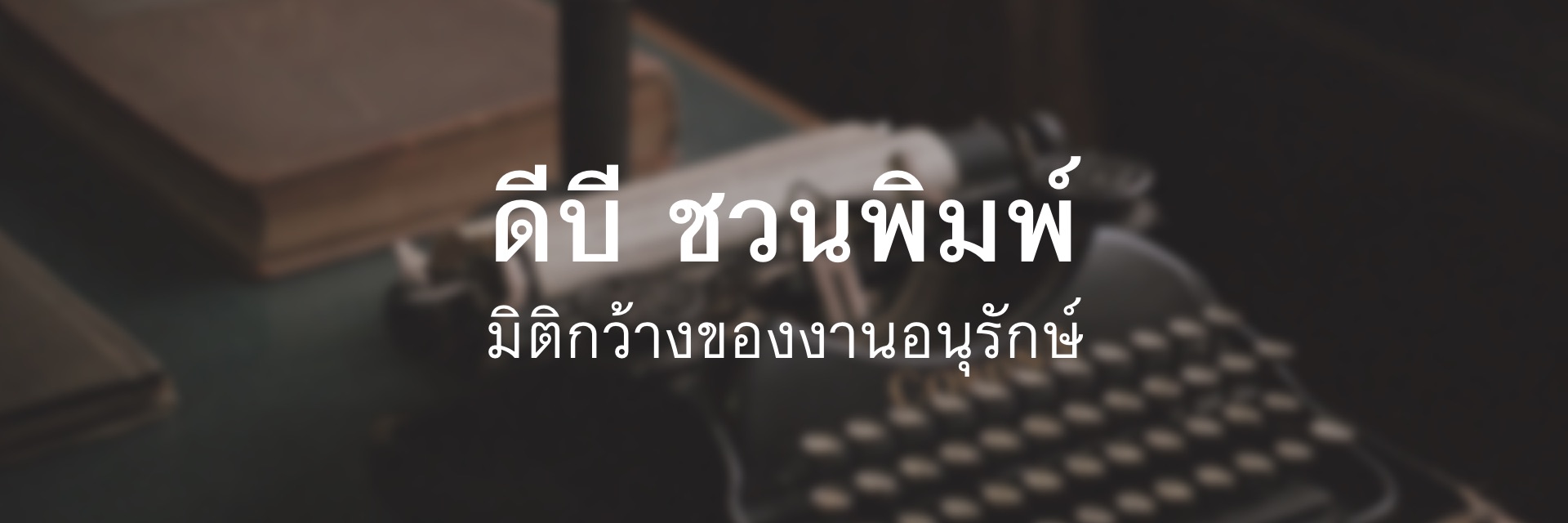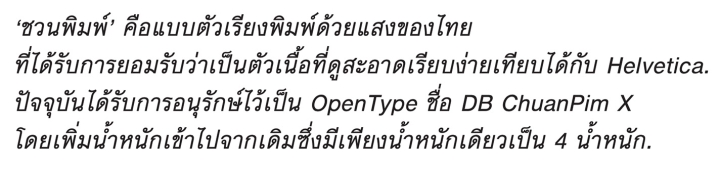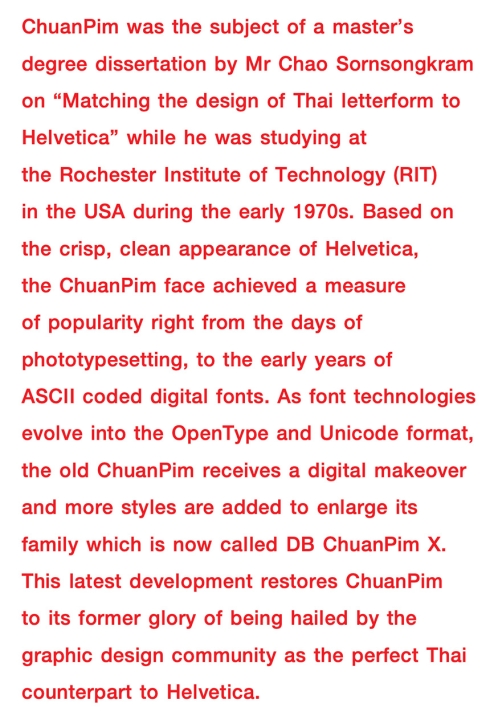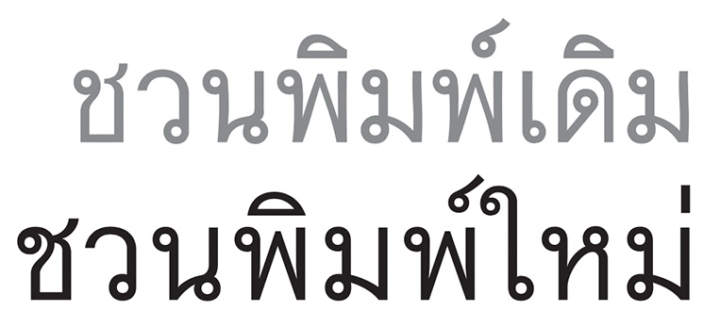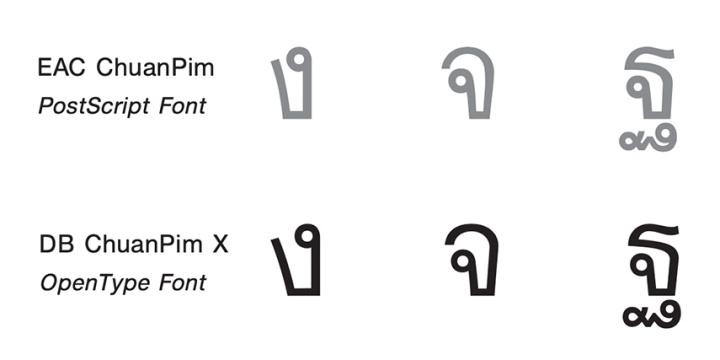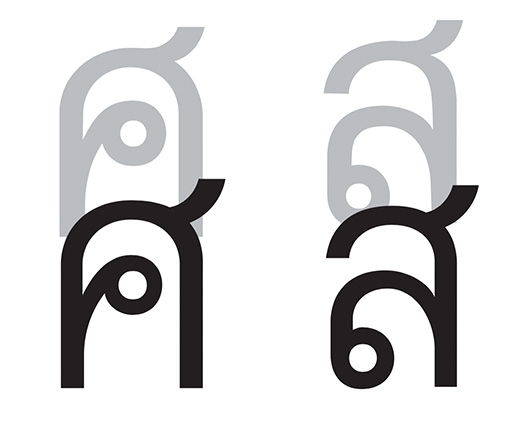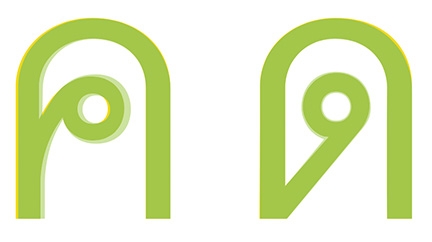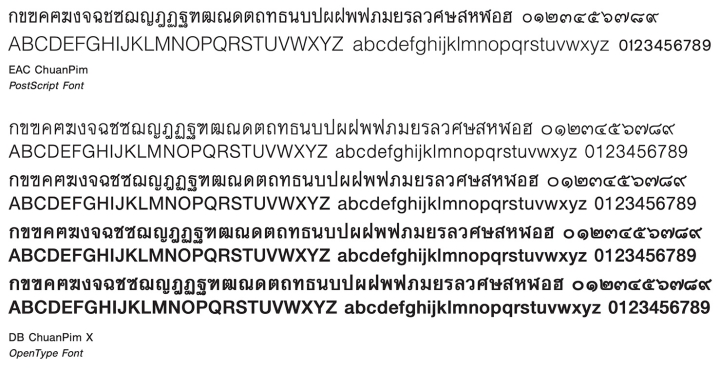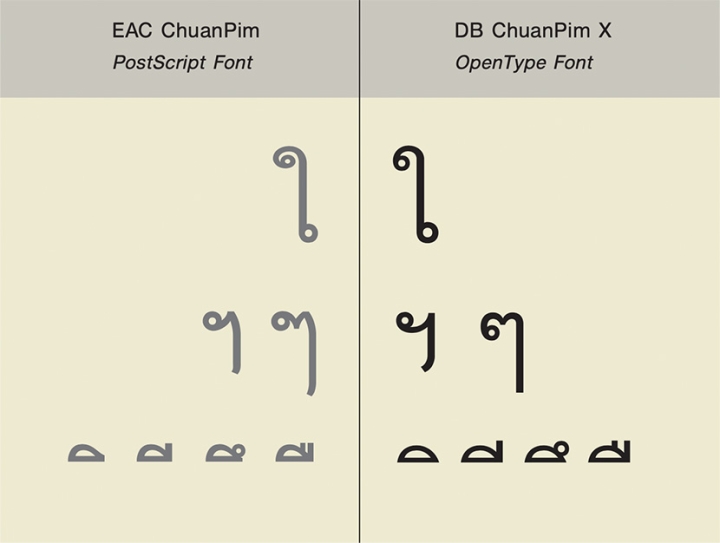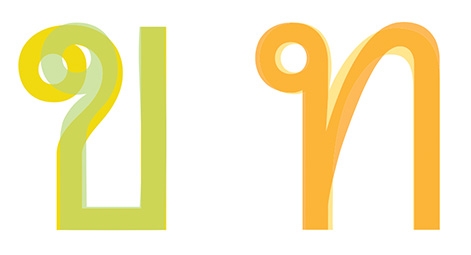
ชวนพิมพ์ต้นแบบเป็นผลงานศิลปนิพนธ์เรื่อง “การออกแบบตัวเนื้อไทยให้สอดคล้องกับ Helvetica” ของ อ.เชาวน์ ศรสงคราม ขณะทําปริญญาโทที่ Rochester Institute of Technology (RIT) ประเทศสหรัฐอเมริกา. ต่อมาได้กลายเป็นตัวพิมพ์เชิงพาณิชย์ที่เลื่องชื่อราวปี พ.ศ.2523 ซึ่งอยู่ในช่วงปลายยุคตัวเรียงพิมพ์ด้วยแสงของไทย. ลักษณะเด่นที่เห็นได้ชัดของชวนพิมพ์คือมีปลายเส้นตัดจบในแนวราบ (horizontal endings) เหมือน Helvetica.
เมื่อเทคโนโลยีเปลี่ยนเข้าสู่ยุคของฟอนต์ดิจิตอลที่เป็น PostScript บริษัท อีสต์เอเชียติ๊ก (ประเทศไทย) จํากัด ผู้แทน จําหน่ายเครื่องเรียงพิมพ์ Compugraphic เดิม ได้ว่าจ้างให้ Dear Book Co., Ltd. ที่มีผมและเพื่อนๆ เป็นเจ้าของ โยกย้ายชวนพิมพ์มาเป็น PostScript Font ที่ใช้กับเครื่องแมคอินทอช ด้วยชื่อ EAC ChuanPim เพื่อใช้กับเครื่อง Imagesetter.
วันที่ต้นแบบโบร์ไมด์ชุดตัวอักษรชวนพิมพ์ขนาดโตถูกส่งมายังบริษัท คุณสุรพล เวสารัชเวศย์ เพื่อนของผมที่ทําหน้าที่ย้ายสํามะโนครัวชวนพิมพ์ และผมต่างดูด้วยความงุนงงว่าทําไมเส้นแนวตั้งของรูปอักษรทั้งชุดถึงได้โค้งงอไม่เป็นเส้นตรง! (เดิม ที่เคยใช้เป็นตัวเรียงคอมพิวจะอยู่แค่ 12-16 ปอยต์ ซึ่งเล็กจนไม่เคยสังเกตเห็น) แต่จะเป็นด้วยข้อสัญญาที่คุณสุรพลทําไว้กับ EAC หรือสไตล์การทํางานของคุณสุรพลเองผมก็ไม่ทราบ ที่ทําให้เขาเพียรพยายามรักษารูปอักษรดั้งเดิมของ อ.เชาวน์ ไว้ทุกประการซึ่งเป็นประโยชน์อย่างยิ่งต่อการใช้พิมพ์อ้างอิงได้ง่าย ในปัจจุบัน.
เส้นแนวตั้งที่โค้งงอในชวนพิมพ์เดิม เป็นการตีค่าของ อ.เชาวน์ ศรสงคราม ให้แฝงความอ่อนช้อยแบบ Helvetica ถูกปรับใหม่ให้เหยียดตรง เพื่อใช้งานในขนาดโตได้เรียบร้อยขึ้น
อย่างไรก็ตาม EAC ChuanPim ในยุคดิจิตอลกลับไม่ได้รับความนิยมมากเท่าที่ควร. สาเหตุอาจเป็นเพราะในต้นยุคดิจิตอลของไทย Dear Book ได้ออกแบบฟอนต์ตัวเนื้อ PostScript ใหม่ๆ คือ DB ThaiText, DB FongNam และ DB Narai* ตามลําดับ ให้คนในวงการใช้ล่วงหน้าไปก่อน จนเกิดกระแสเห่อของใหม่ลืมคุณค่าตัวเก่าๆ ไป. อีกสาเหตุคงเป็นที่ ปัญหาของ EAC ChuanPim เอง ซึ่งมีเพียงตัวปรกติให้ใช้แค่น้ําหนักเดียว ประกอบกับแนวโน้มความนิยมตัวเนื้อที่โปร่งบางขึ้น และขนาดค่อนข้างจะเล็กลง, ทําให้ “สี” ของ EAC ChuanPim ดูออกจะเข้มมากไปเสียแล้วที่จะเป็นตัวเนื้อ.
ช่วงที่ผมได้รับเชิญจากชมรมการจัดพิมพ์อิเล็กทรอนิกไทย ให้ไปเป็นวิทยากรกล่าวนําหลักการออกแบบตัวพิมพ์เบื้องต้นให้ แก่ผู้เข้าร่วมประกวด 10 แบบตัวพิมพ์ไทยเพื่อการแจกฟรีชุดแรกนั้น นับว่าเป็นโชคของผมที่ได้มีโอกาสได้พบ อ.เชาวน์ และต่อมาได้เข้าฟังคําบรรยายของท่าน เรื่อง Negative Space และ Positive Space ในตัวพิมพ์ไทย ร่วมกับนักออกแบบที่ได้รับการคัดเลือก อ.เชาวน์ ได้ยกตัวอย่างตัวพิมพ์ ‘ศิริชนะ’ ของ อ.วันชัย ศิริชนะ ให้ดูว่าเป็นแบบอย่างที่ดีของการให้ความสําคัญ ‘พื้นที่ว่าง’ ในตัวพิมพ์แต่ละตัว และก็นับเป็นโชคดีอย่างยิ่งของผม เมื่อครั้งที่เป็นตัวแทนของสมาคมนักออกแบบเรขศิลป์ไทย (ThaiGA) เข้าร่วมประชุมกับสํานักงานศิลปวัฒนธรรมร่วมสมัย (สศร.) นั้น ผมมีโอกาสได้ฟังผู้ใหญ่ครูบาอาจารย์หลายท่านในวงการศิลปวัฒนธรรมร่วมสมัยไทย อภิปรายเกี่ยวกับพันธกิจของ สศร. ทําให้ผมชัดเจนกับนิยามของงานอนุรักษ์มากขึ้นว่า ไม่จําเป็นต้องเหมือนเก่าเสียทั้งหมด แต่สามารถปรับแต่งเพื่อให้ร่วมสมัยขึ้นได้.
ส และ ศ เดิมหางสั้น และซ่อนตัวอยู่เป็นระเบียบเสมอแนวเส้นหลัง ถูกต่อหางเยื้องเลยไปทางซ้ายเพื่อให้อ่านได้ง่ายขึ้น
งานอนุรักษ์ชวนพิมพ์ ในปี พ.ศ.2550-2551 ของผมเกิดจากการต่อยอด EAC ChuanPim ที่คุณสุรพลทําไว้. ผมใช้หลักการสร้างสมดุลในพื้นที่ว่างของ อ.เชาวน์ และทฤษฎีคู่สับสนของผมเองในการปรับปรุงชวนพิมพ์ด้วย ‘มิติที่กว้างขึ้น’ ของงานอนุรักษ์.
รายการแรกสุดที่ต้องทําคือ จัดการปรับเส้นแนวตั้งทั้งหมดให้เป็นเส้นตรง เพื่อให้ดูเป็นระเบียบเรียบร้อยเมื่อใช้ในขนาดโตๆ. จากนั้นเมื่อพิจารณาพื้นที่ว่างของตัวที่ค่อนข้างแคบ เช่น ง, จ, ฐ จะถูกดึงออกให้กว้างขึ้นเล็กน้อย. หรือกลุ่มอักษรที่หัวถูกปิดล้อมด้วยเส้นหน้า เส้นหลัง เช่น ค, ด ฯลฯ หัวจะถูกลดขนาดให้บางลงเพื่อเพิ่มพื้นที่ว่างให้ดูโปร่งขึ้น. ชุดสระ บน อิ อี อึ อื ก็เช่นกัน ถูกขยายพื้นที่ว่างภายในเพื่อลด ‘มวล’ ของมันลงไม่ให้ดูกดทับตัวพยัญชนะข้างล่าง. แม้แต่ขมวดม้วนของไม้ม้วนเดิมที่สวยงามเป็นเอกลักษณ์ของชวนพิมพ์ ผมก็ต้องตัดใจทําให้มันโปร่งขึ้น เพื่อเปิดโอกาสให้เพิ่มน้ําหนักเป็นตัวหนาขึ้นได้โดยไม่ทึบตัน.
ชุดตัวพิมพ์ของ อ.เชาวน์ ค่อนข้างสมบูรณ์ในแง่การอ่านอยู่แล้ว กล่าวคือ มีคู่สับสนกันอยู่น้อยมาก เช่น ล-ส และ ค-ศ เนื่องจากหางสั้น และซ่อนตัวอยู่เป็นระเบียบเสมอแนวเส้นหลัง (เป็นการจัดระเบียบด้วยหลักคิดของ Helvetica) ถ้ามีสระบนกํากับอยู่จะสังเกตหางได้ยากในขนาดปอยต์เล็กๆ จึงถูกต่อหางเยื้องเลยไปทางซ้ายเพื่อให้อ่านได้ง่ายขึ้น เครื่องหมายไปยาลน้อย ‘ฯ’ เดิมซึ่งดูคล้ายเครื่องหมายไม้ยมก ‘ๆ’ มาก ถูกปรับพื้นที่ว่างระหว่างหัวกับเส้นดิ่งให้เห็นชัดว่าไม่มีส่วนหยักแบบ ‘ๆ’ รวมทั้งหดหางให้เสมอเส้นฐานเพื่อให้ดูแตกต่างจาก ‘ๆ’ ซึ่งยาวเลยเส้นฐาน (ตามมาตรฐานฟอนต์ตระกูล DB)
ในอักษรบางตัวของชวนพิมพ์เดิม เช่น ข และ ท แม้จะไม่สับสนกับตัวใดๆ แต่เพื่อให้กวาดสายตาอ่านได้ง่าย จึงได้เพิ่มขนาดส่วนหัวขมวดม้วนของ ข. และเพิ่มความทแยงของเส้นกลาง ท. ให้ดูชัดเจนยิ่งขึ้น.
ค, ด หัวจะถูกลดขนาดให้บางลงเพื่อเพิ่มพื้นที่ว่างให้ดูโปร่งขึ้น
นอกจากรายละเอียดที่ผมกล่าวไปแล้ว ส่วนสําคัญอย่างยิ่งคือ การเพิ่มช่องไฟระหว่างตัวอักษรเข้าไปให้มากกว่าเดิม เพื่อ ให้อ่านได้ง่ายในขนาดตัวจิ๋ว หรือแม้กับตัวเนื้อขนาดปรกติก็ตาม ที่ถูกบีบให้อยู่ในคอลัมน์แบบเสมอหน้า-หลัง, ชวนพิมพ์ใหม่ น้ําหนักปรกติเมื่อเสร็จออกมาจึงดูโปร่งกว่า EAC ChuanPim ทั้งที่ความหนาของเส้นแนวตั้งยังคงเดิม. เพื่อให้สมกับตัวเนื้อไทยที่เทียบเคียงกับ Helvetica ผมจึงตัดสินใจขยายสมาชิกออกไป มีทั้งตัวบาง, ตัวค่อนข้างหนา และตัวหนา พร้อมชุดตัวเอน รวมเป็น 8 สไตล์
ผมได้ไปเยี่ยม อ.เชาวน์ พร้อมแบบทดสอบพิมพ์ของชวนพิมพ์ทั้งชุดที่เป็น OpenType เพื่อขอคําแนะนํา เมื่อได้เห็นชวนพิมพ์หลายน้ําหนักปรากฏอยู่ตรงหน้า ผมสังเกตเห็นรอยยิ้มอย่างมีความสุขของอาจารย์
“เคยมีคนเอาชวนพิมพ์ไปทําเป็นเส้นบางๆ มาให้ผมใช้” อาจารย์เล่าให้ฟัง “รู้สึกสบายตากว่าของเดิมของผมเสียอีก”
“ผมจะใช้ชื่อว่า ดีบี เชาวน์ ดีมั้ยครับอาจารย์?” ผมถามนํา ด้วยความตั้งใจจะให้เครดิตกับผู้ออกแบบ
“ชื่อ ชวนพิมพ์ อย่างเดิมดีกว่าครับ” อาจารย์ตอบด้วยรอยยิ้ม ผมจึงพยักหน้าตามนั้น.
สิ่งที่ผมได้เรียนรู้จากอาจารย์ในวันนั้นคือ ความใจกว้างและความถ่อมตน ทําให้คนน่าเคารพนับถืออย่างยิ่ง. คํากล่าวที่ว่า ‘คบคนพาล พาลพาไปหาผิด คบบัณฑิต บัณฑิตพาไปหาผล’ เป็นสัจธรรมเสมอ. ทั้งคําบรรยายของ อ.เชาวน์ และนิยามที่ กว้างขึ้นของการอนุรักษ์จาก สศร. ที่ผมได้ซึมซับมา ล้วนมีส่วนสําคัญที่ทําให้งานอนุรักษ์ ‘ชวนพิมพ์’ ของผม ประสบผลเป็นที่น่าพอใจ…
ในสายตาของ อ.เชาวน์ ผู้ให้กําเนิด “ชวนพิมพ์” เอง.